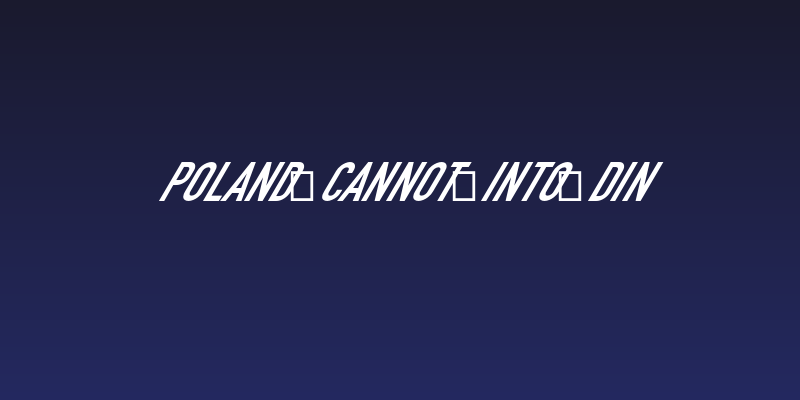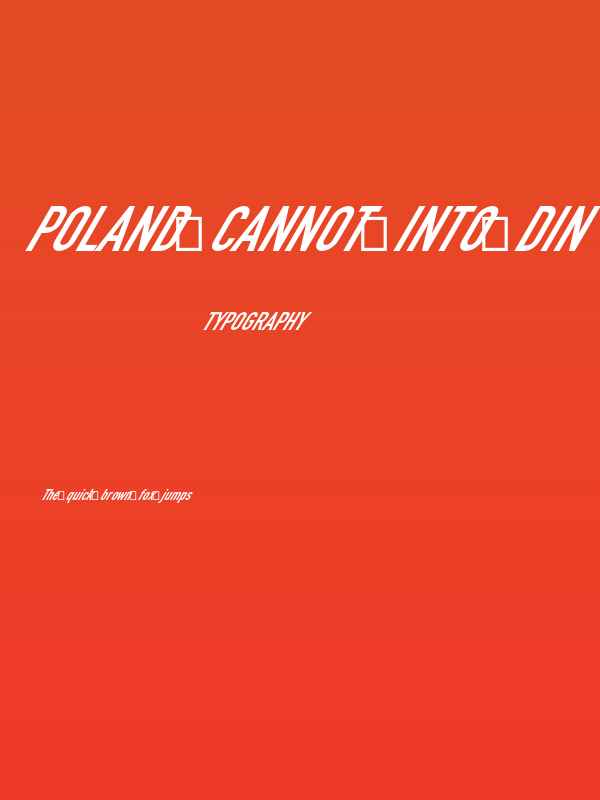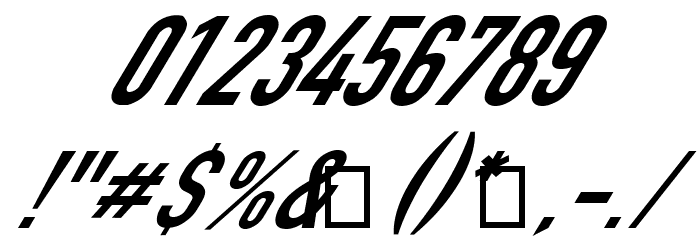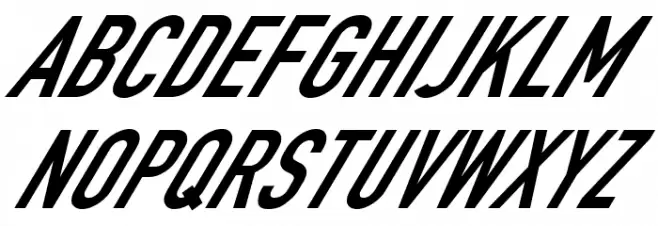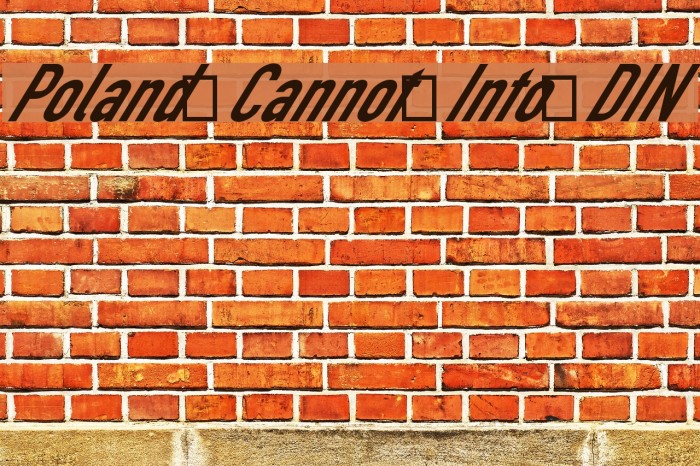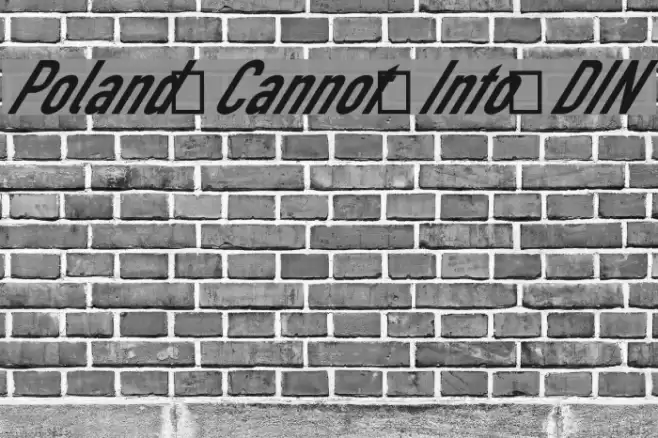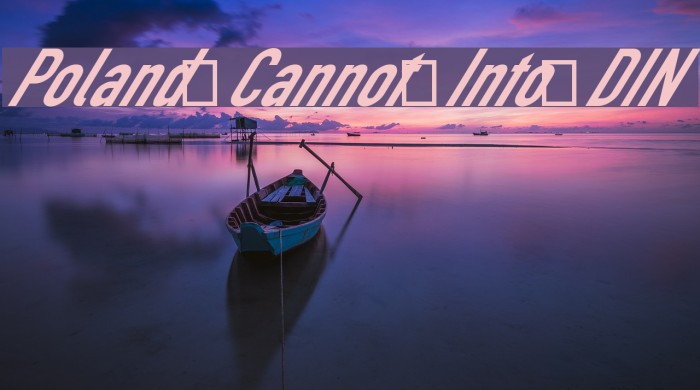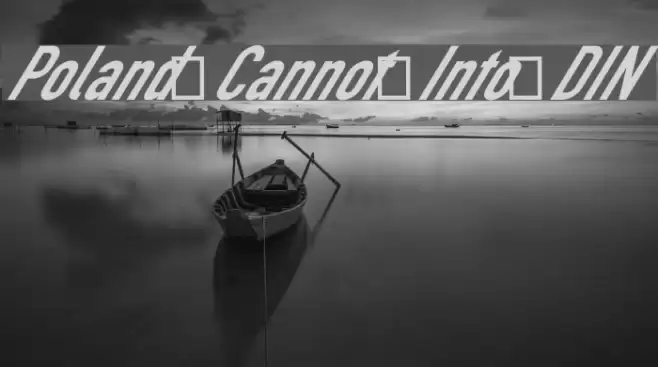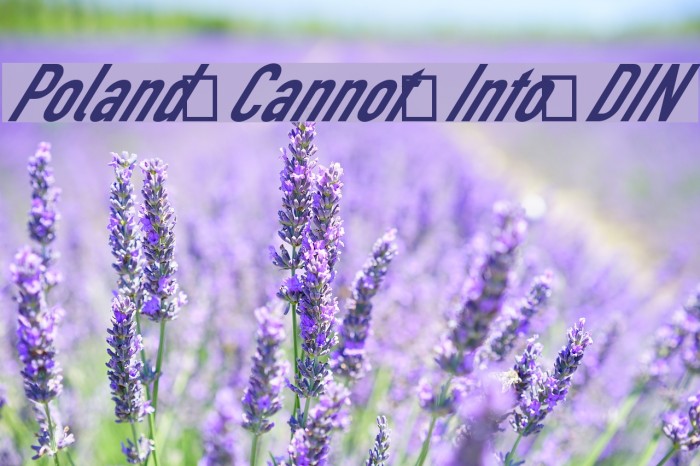
Poland Cannot Into DIN Font
✎ Thick
| الفئات | Thick |
| مائل | Yes |
| حالة الاستخدام | Headlines, Logos, Advertising |
| مشاريع مقترحة | Ideal for branding, advertising, and headlines where a strong and modern impact is desired. |